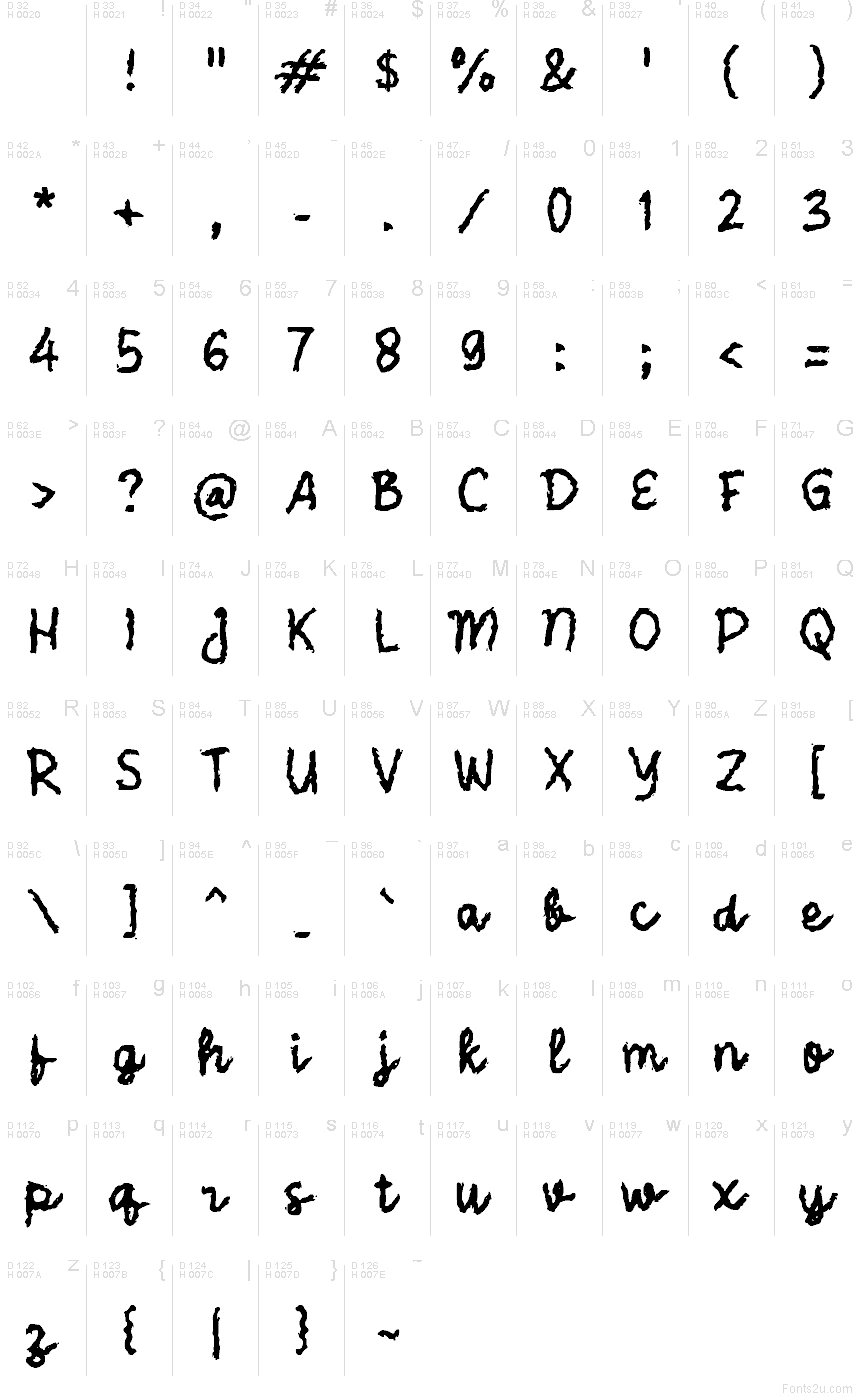
Sabraon Rough
Sabraon Rough da Wep é uma fonte "trash" gratuita, definida por formas inchadas que lembram tinta e espaços internos rasgados, que fazem as letras parecerem roídas em vez de apenas desgastadas. A aspereza parece orgânica e irregular em todo o design, dando-lhe uma textura suja e low-fi com bordas ligeiramente derretidas.
Faz todo o sentido para flyers de música underground, títulos de filmes de terror, capas de zines, posters com estilo bruto e gráficos de jogos que precisam de algo cru, em vez de polido. A superfície fragmentada mantém os títulos curtos ativos e inquietantes, enquanto a silhueta preta e robusta dá aos logótipos e designs de embalagens peso gráfico suficiente para se manterem coesos.